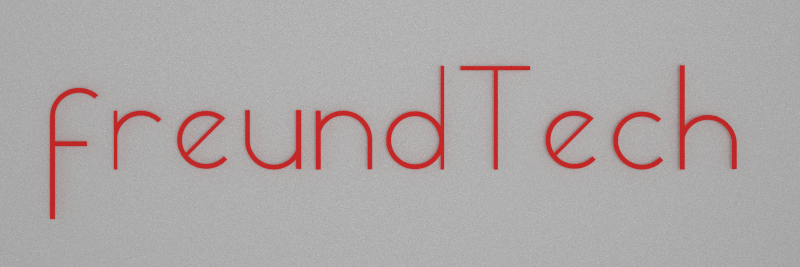
Suche diese Schrifftart:
vor einiger Zeit habe ich in einer 3D-Animation eine bestimmte Schrifftart aus dem Internet verwendet. (Bild ist an diesen Post angehängt)
Nun benötige ich die Schrifft erneut, kann sie aber weder auf meinem PC, noch im internet finden.
Kenn hier jemand zufällig den Namen dieser Schrifftart? Falls nicht: Kennt jemand eventuell eine ähnliche Schrifftart? Besonders wichtig ist mir dabei die Form des "f".
Besonders wichtig ist mir dabei die Form des "f".